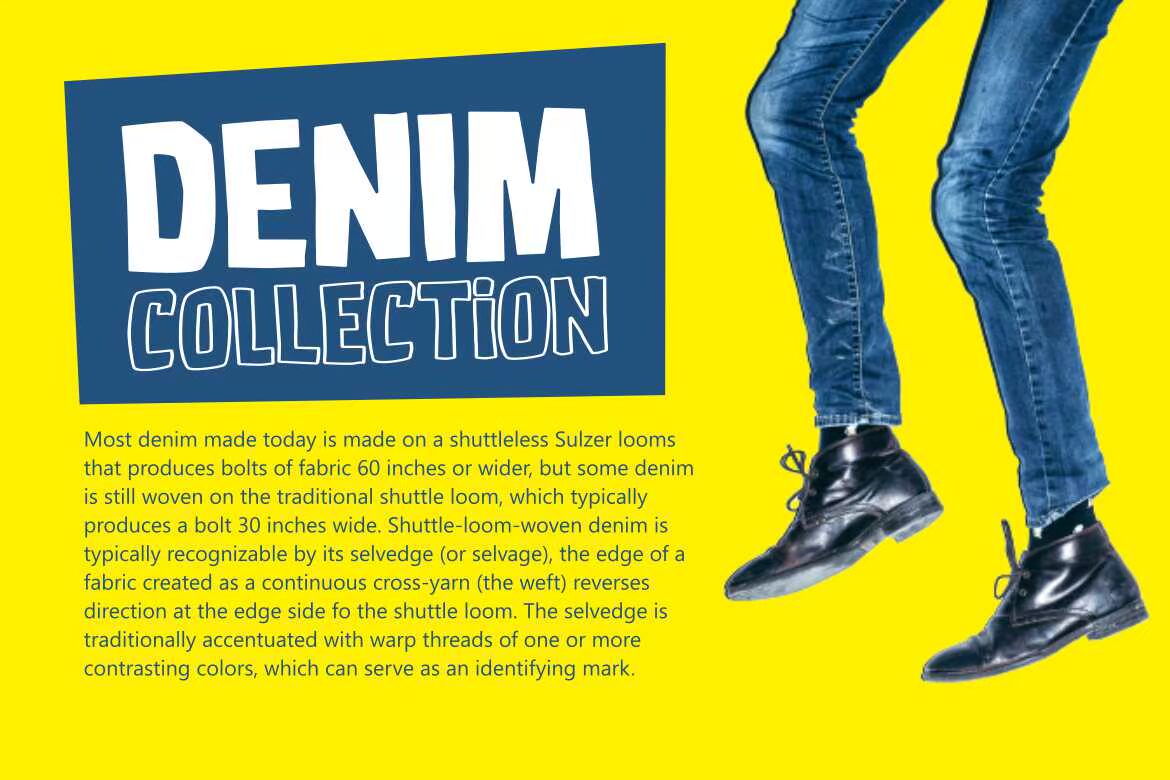
Djadoelisa QuirkyFonthaggoodoldmemories and smilestood surface.有2种样式,规则和外线。大写和小写字母之间的Subtle Liganization将包含所有项目。Djadoelisa QuirkyFonthaggoodoldmemories and smilestood surface.有2种样式,regulerandoutline.大写和小写之间的SubtleLiganization将在您拥有的所有项目中显示。